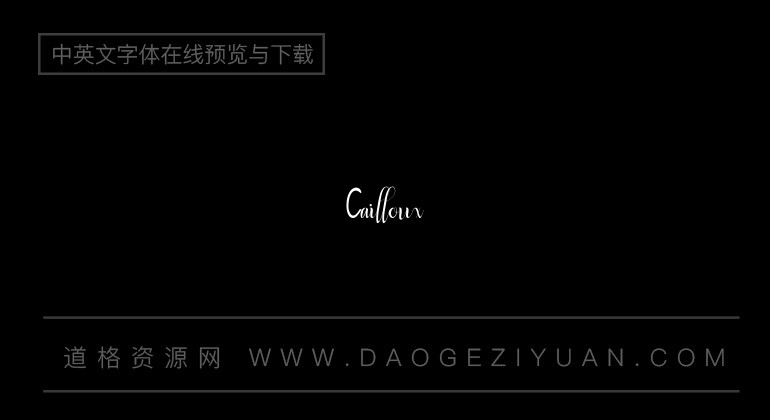
Cailloux 是一种装饰性的手写风格字体,由法国设计师 Sabrina Lopez 创作。这种字体结合了手写字和书法艺术的特点,在视觉上具有古典和优雅的感觉。 Cailloux 字体的特点是其流畅和优美的线条,以及字母的呈现方式,每个字母都似乎是手写而成。这种字体的笔画非常细腻,从而使得每个字母看起来都是独一无二的。 Cailloux 字体可用于各种场合,例如设计卡片、海报、广告和网站等。由于其独特的风格,它可以为你的设计增添自由、艺术的感觉。内容介绍
Cailloux是一款非常不错的手写艺术字体,具有很好的视觉感,适合于文化类的宣传设计、商业类品牌的广告和产品包装设计以及个性化文字排版等较多场景。